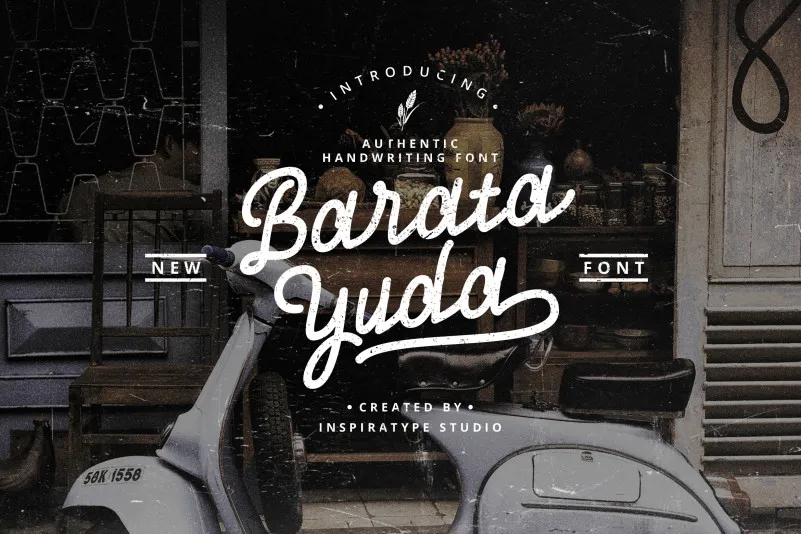
Baratayuda Authentic Handwriting Font – Download Grátis
A fonte “Baratayuda Authentic Handwriting Font” é uma criação que transporta você para ambientes únicos e envolventes, perfeitamente adaptada aos desafios do design de letras manuscritas. Inspirada nos postais clássicos, essa fonte foi meticulosamente escrita à mão, oferecendo uma variedade incrível de alterações em cada caractere para criar um estilo único e personalizado. Ela inclui alternativas da OpenType, ligaturas comuns e até mesmo swashes adicionais, tudo isso com o objetivo de permitir que você personalize as suas criações conforme desejar. Perfeita tanto para logotipos quanto para etiquetas, cartões de carta e materiais de apresentação, “Baratayuda Authentic Handwriting Font” é uma escolha ideal. Suas características fluidas e elegantes garantem um toque artesanal inconfundível em qualquer design que você criar. Seja para aplicativos digitais ou impressos, esta fonte oferece a capacidade de adicionar sofisticação e originalidade à sua marca ou projeto. Sua facilidade na criação de logotipos, letrinhas de cartão, painéis publicitários, design de roupas, etiquetas, e muito mais, é um verdadeiro prazer explorar as possibilidades criativas que esta fonte oferece.